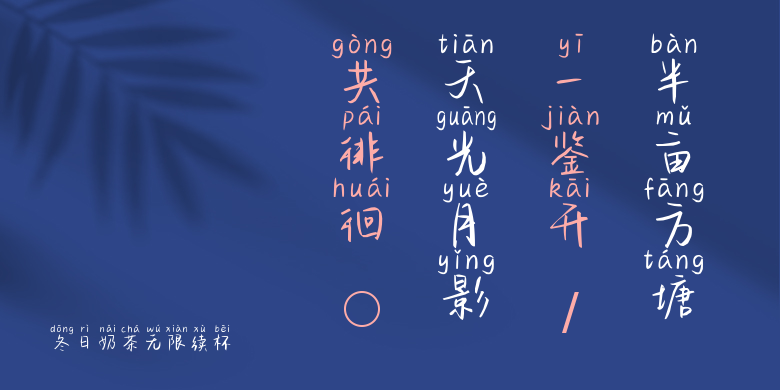
冬日奶茶无限续杯
冬日奶茶无限续杯,这款字体结构工整、笔画清晰,兼顾美观与易读性,适用于标题、正文、海报、包装、LOGO 等多种场景。字形优雅稳定,风格百搭耐看,适配日常排版与创意设计,让文字呈现更舒适、更具质感。冬日奶茶无限续杯一笔一画,皆是细节,以均衡的比例、流畅的线条打造舒适视觉体验,字形端正大气,风格简约现代。无论是商业设计、品牌宣传还是日常排版,都能轻松驾驭,让文字更有格调与力量。冬日奶茶无限续杯字体下载。